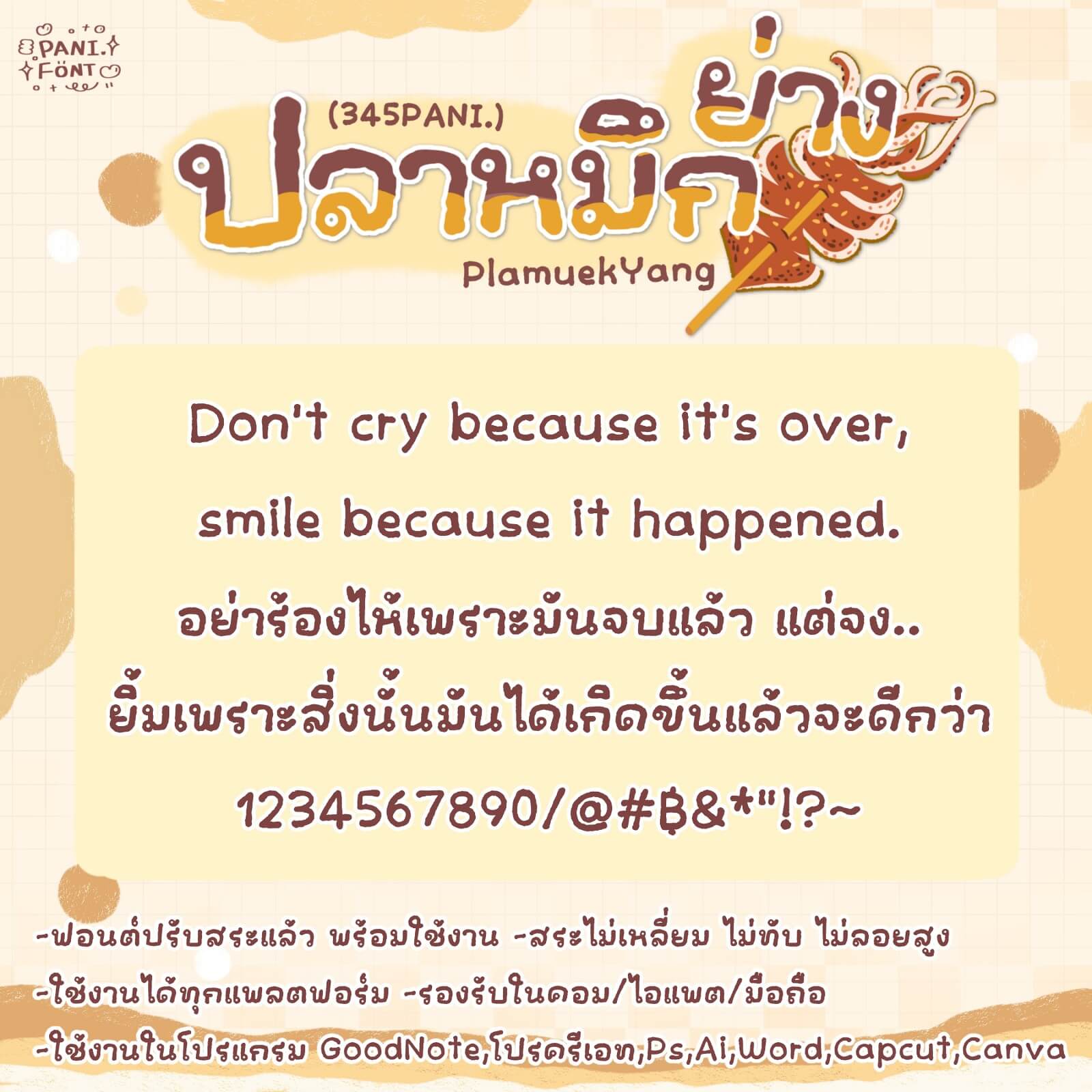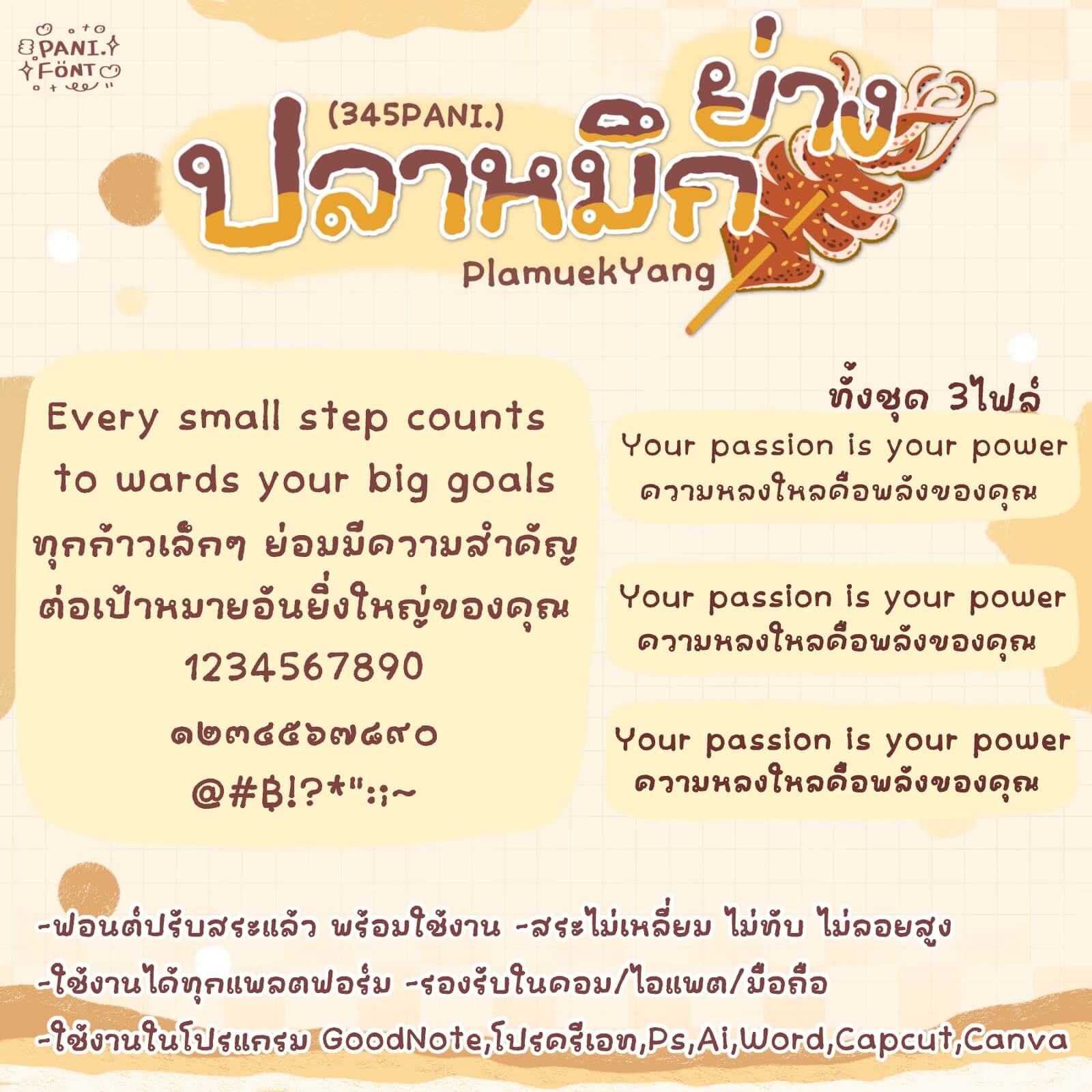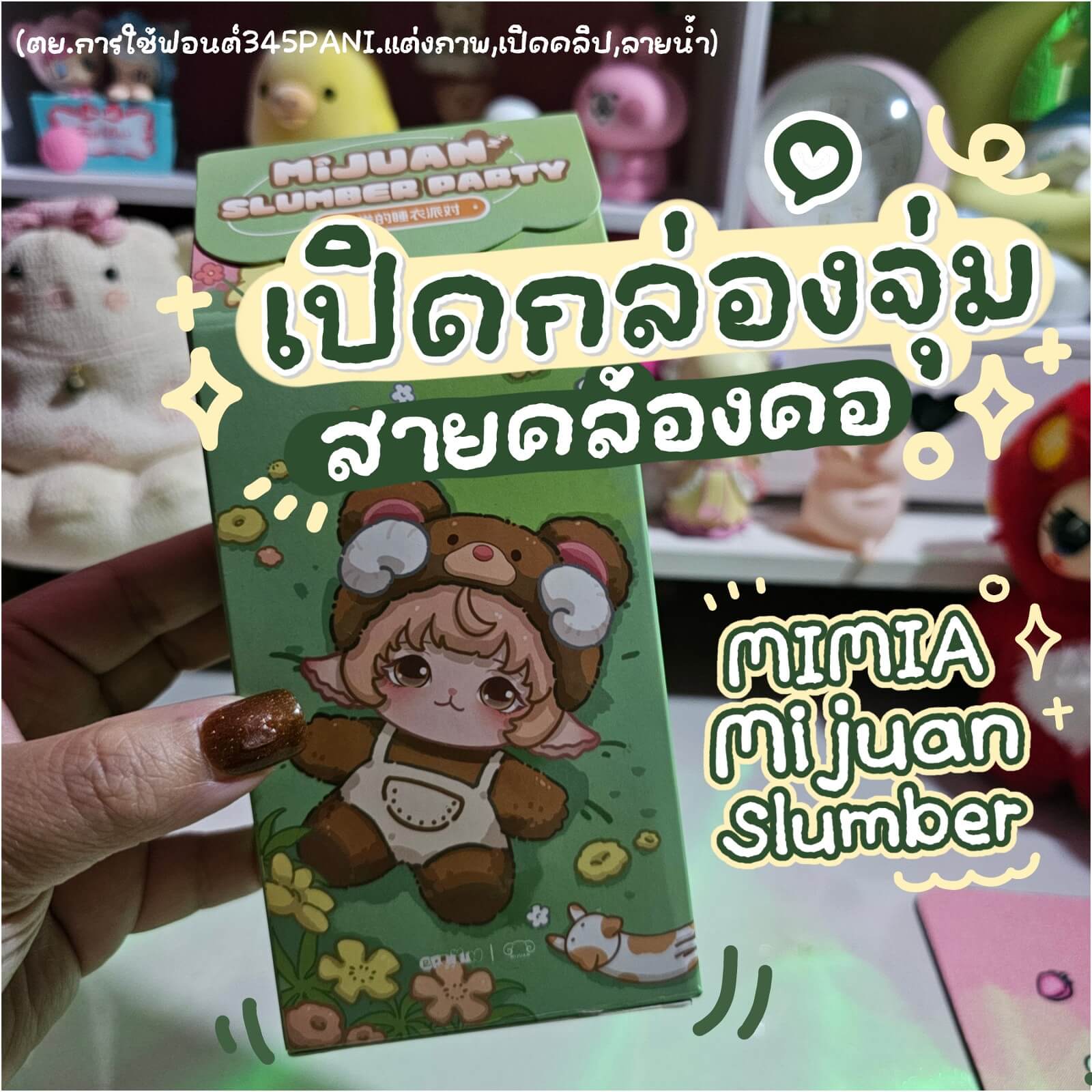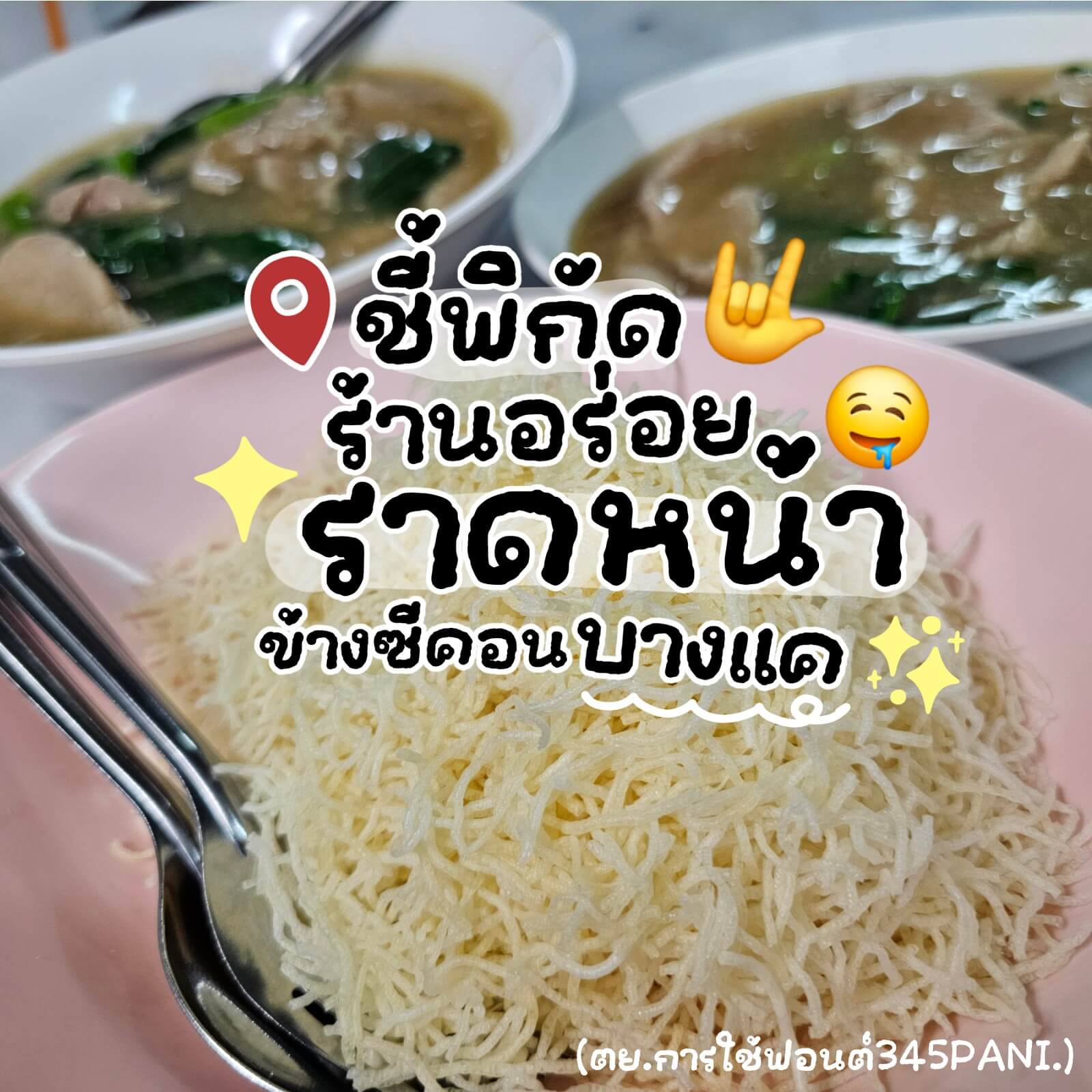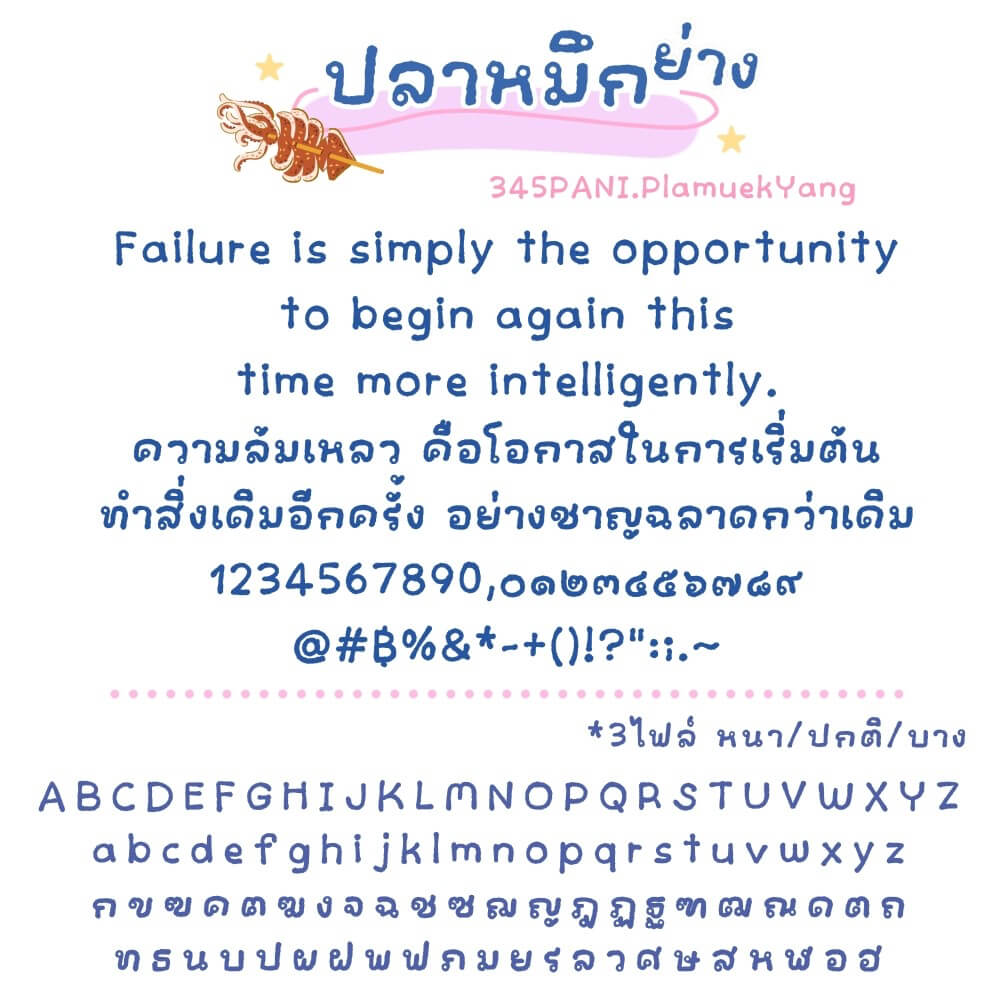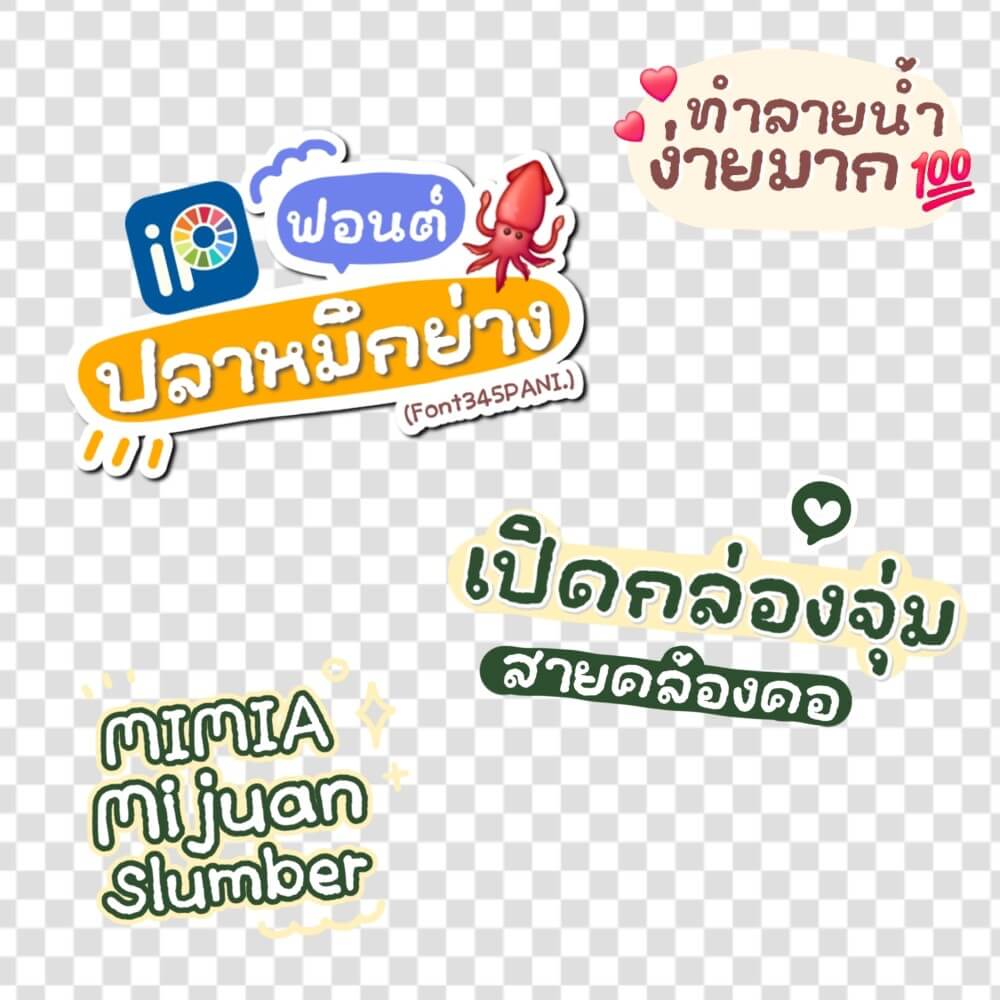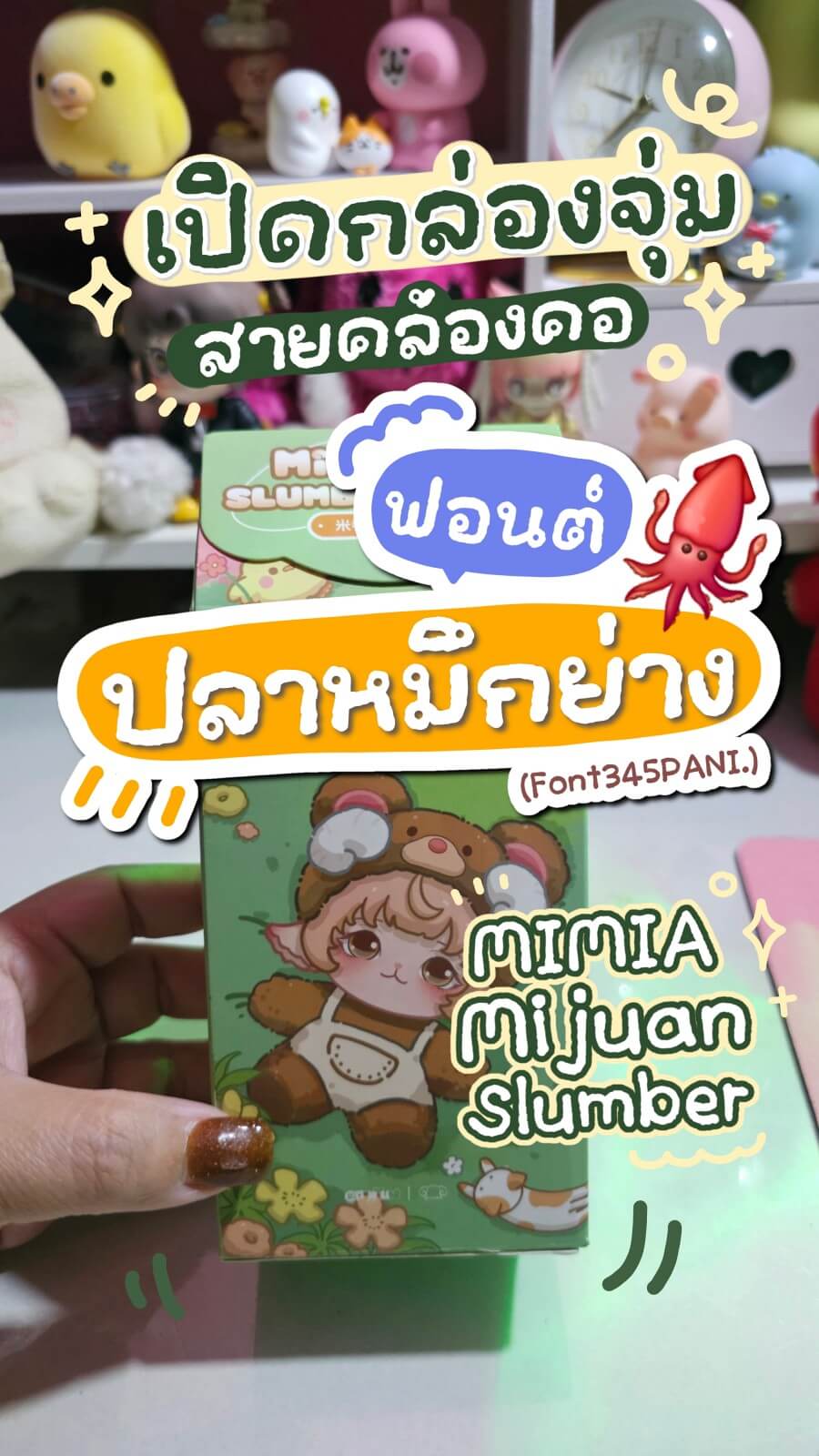
345PANI.ปลาหมึกย่าง
ฟอนต์ 345PANI.ปลาหมึกย่าง – ฟอนต์นี้ดีจริงๆ สายทำคลิป เพิ่งหัดทำ ทำให้งานง่ายขึ้นมากเลยค่ะ ฟอนต์ดีมีชัยไปกว่าครึ่ง❤
ฟอนต์น่ารัก อ่านง่าย ทันสมัย ตัวฟอนต์มีเท็กซ์เจอร์ เมื่อขยายใหญ่จะเห็นชัด ทำให้งานดูละมุน โดดเด่นน่าสนใจ แต่งภาพ แต่งคลิปง่าย เหมือนมืออาชีพ *ครีเอเตอร์/นายหน้า ต้องถูกใจ* สายตั้งเป็นฟอนต์เครื่อง อ่านสบายตาแน่นอนค่ะ